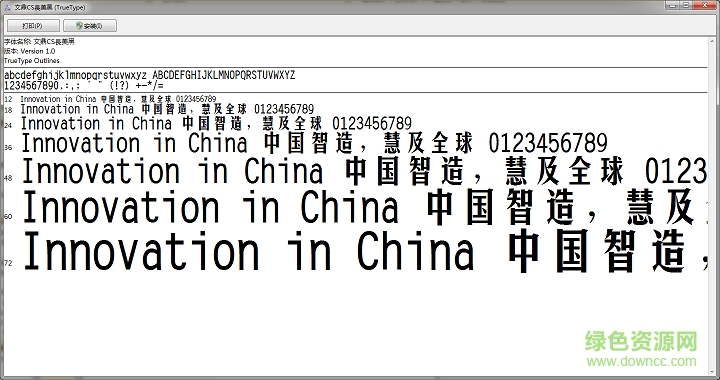
chunmeiheicseg字體又叫文鼎CS長美黑字體,是一款修長型的黑體字體,優(yōu)雅美觀又實(shí)用,還富有古典藝術(shù)氣息,也是大多數(shù)用戶在進(jìn)行書面內(nèi)容排版時(shí)比較常用的字體之一,非常的端莊整潔,喜歡這類字體的小伙伴快來綠色資源網(wǎng)下載吧!
它具有字體勻稱、清秀美觀的特點(diǎn),給人端正又正氣的視覺效果,可適用于標(biāo)題類文字輸入。